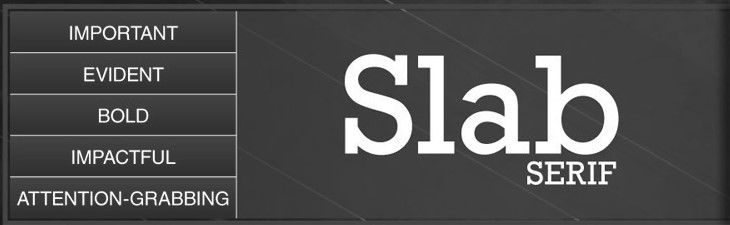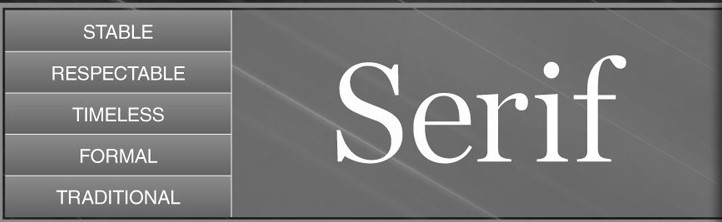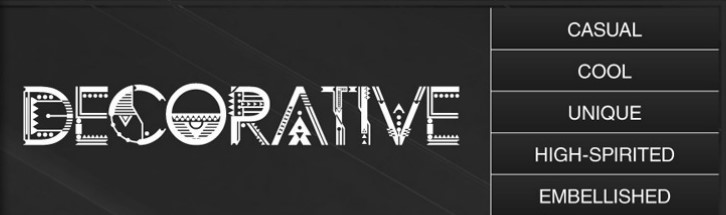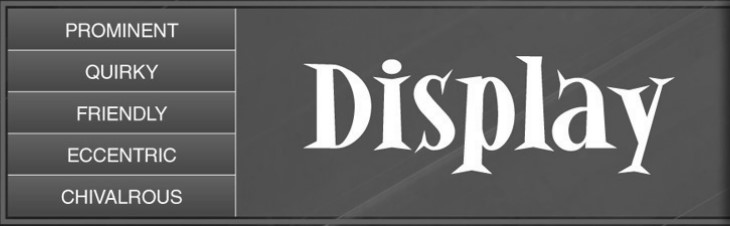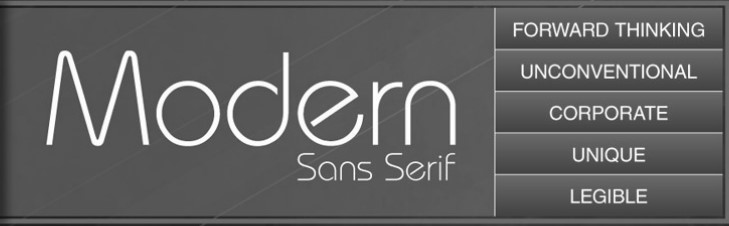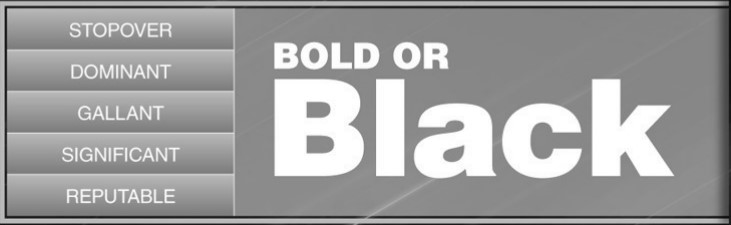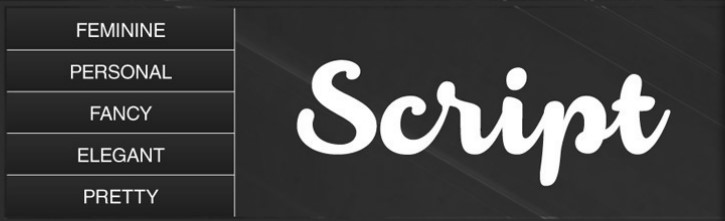
Proč PSYCHOLOGIE FONTŮ®?
PROTOŽE NA FONTU ZÁLEŽÍ!
Věděli jste, že správným výběrem fontu můžete skrz jeho vizuální působení neverbálně komunikovat své hodnoty a lépe tak oslovit své ideální klienty?
I. FONTY V GRAFICE A WEBDESIGNU
„Pouhou" změnou fontu dosáhnete často mnohem víc, než dlouhým laděním barev a obrázků. Jedním kliknutím dokážete změnit emoce, atmosféru i vyznění textu. Obsah nestačí, text potřebuje i správnou formu.
„Jako webdesignerka se setkávám s výběrem fontů velmi často. Vždy jsem k nim přistupovala obezřetně a s respektem, ale spíše tak, abych nevhodným fontem "nepokazila" celkový design webu. V grafice mám ráda čistotu a minimalismus, takže jsem v 90% případů skončila u jednoduchých bezpatkových fontů. Ty totiž nikoho neurazí, ale ani nenadchnou... Až díky Andree jsem objevila, jak velký rozdíl může udělat font "na míru" s designem a celkovou náladou webu.“
„Font, použitý na webu nebo na vizitce, vyjadřuje osobitost, ovlivňuje vnímání a dokresluje celkový dojem. Má moc přitáhnout ty správné klienty a odradit ty ostatní. Dovoluje vyjádřit atributy, jako je důvěra, jednoduchost, péče, něžnost nebo síla. Proto dává smysl věnovat volbě fontu stejnou pozornost jako výběru barev, ilustračních fotografií nebo sloganu. A proto považuji psychologii fontů za velmi užitečný marketingový nástroj. “
II. FONTY V MARKETINGU
Font sám o sobě má obrovskou moc ovlivnit vnímání čtenářů a tím i to, jestli vám budou věřit nebo ne. Dokáže budit emoce i oslovit konkrétní cílovou skupinu. Na webu, na sociálních sítích i v reklamě.
III. FONTY A BRANDING
Font je nedílnou součástí vizuální identity firmy či podnikatele a stojí za to si ho vybrat s jasným záměrem. Podporuje hodnoty značky, zdůrazněním jedinečných kvalit ji odliší od konkurence a vyvolává očekávání a emoce, které značka umí uspokojit.
„Tak ako farby či logo, tak aj font je jedným z elementov, ktoré spoločne tvoria celkovú identitu značky. Aj keď sú fonty často opomínané a vyberané zhurta a na poslednú chvíľu, sú nositeľom najpodstatnejších vlastností brandu. Komunikujú hodnoty, dopĺňajú logo a taktiež dávajú vyniknúť jedinečnosti značky. Mnohokrát sú natoľko špecifické, že na nich stojí celý brand - napríklad CocaColu si bez svojho typického fontu už nevieme ani predstaviť.“